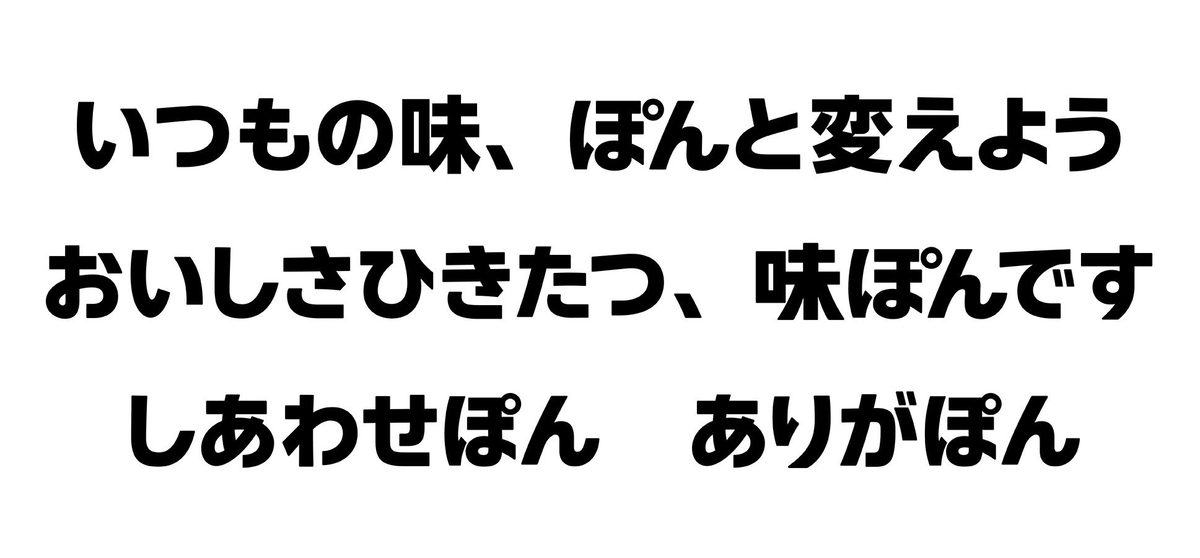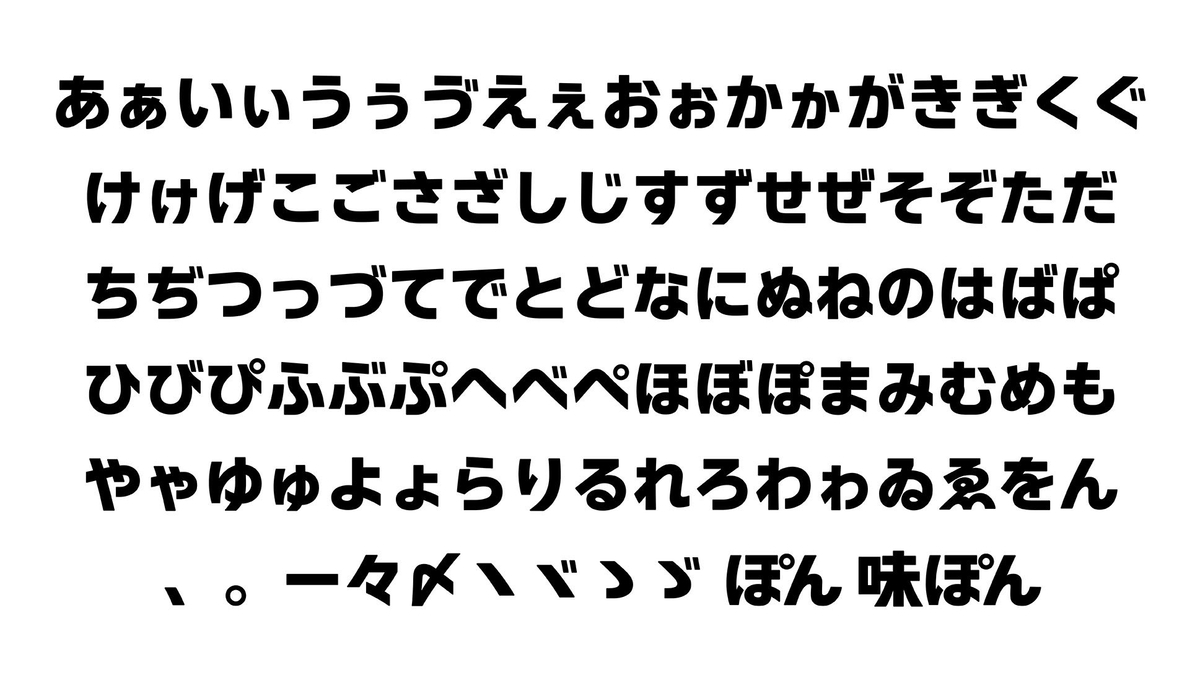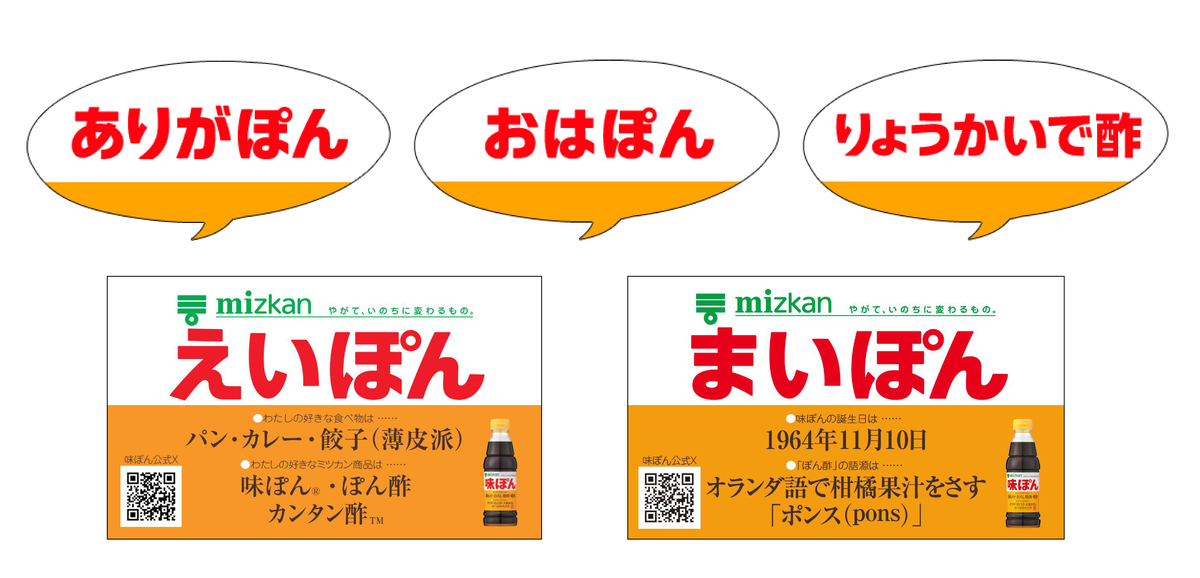
モリサワが60周年キャンペーン開催中のミツカンのぽん酢ブランド「味ぽん」のオリジナルフォント「味ぽんフォント」を開発
モリサワは、Mizkanのぽん酢ブランド「味ぽん」の発売開始60周年の節目に合わせてオリジナルフォント「味ぽんフォント」を開発したことを2024年11月7日に発表した。
味ぽんフォント
1964年11月10日に発売を開始したぽん酢ブランド「味ぽん」は、かんきつ果汁・醸造酢・しょうゆがひとつになった他では味わえない絶妙な風味の調味料として、長年多くの消費者の方に愛されている。開発したオリジナルフォント「味ぽんフォント」は、
2024年で発売60周年の節目を迎える「味ぽん」がこれからも愛され続けるブランドであるために、世界観を守り、より強いブランドにしていくことを目的として、企画、制作されたものでブランドを象徴する商品ロゴの文字をベースとし、ひらがなの95文字に加え「味ぽん」「ぽん」のロゴをフォントとして制作した。
親しみやすさやあたたかみのある文字の印象はそのままに、モリサワのUD(ユニバーサルデザイン)フォント「UD新ゴ」の漢字と混植しても違和感がなく、味ぽんフォントとしての特徴が伝わるようにデザインされている。
漢字にはUD新ゴ Hを使用(合字をのぞく)している。「ぽん」「味ぽん」は合字。
「味ぽんフォント」は、味ぽん発売60周年記念企画として制作されたLINEスタンプや一部関係者の名刺などにすでに使われており、今後もさまざまな使用先が検討されている。
株式会社Mizkanマーケティング本部コミュニケーション戦略部デザインチーム山田英子氏による「味ぽんフォント」へのコメント
味ぽんフォントを作ろうと思ったきっかけは、社内から「名前入りの味ぽんのデザインを作れないか」という相談を受けたことでした。その時は外部のデザイナーさんにお願いし対応したのですが、今後フォントがあれば統一された世界観で、スピーディーに安く対応できるのではと考え、モリサワ様に相談しました。何度もディスカッションし、調整いただいたお陰で、味ぽんのキャラクターを存分に表現したフォントになったと思います。今年60周年を迎えた味ぽんは、「お客様の声を形に」をテーマにさまざまな取り組みを実施中です。今後より広く・深く味ぽんを愛していただけるような企画も検討中ですので、楽しみにしていただければと思います。